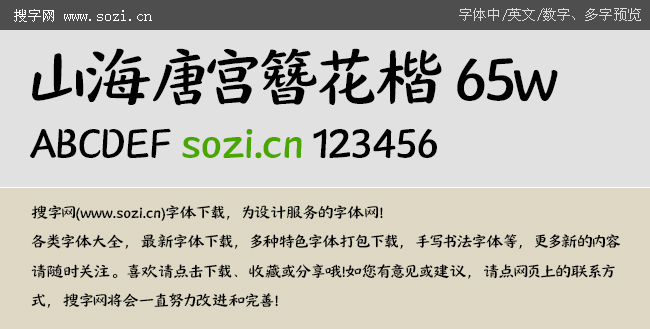
山海唐宮簪花楷 65w
搜字網給大家提供一款山海唐宮簪花楷 65w中文字體下載,山海唐宮簪花楷是一款全新的楷體字體,該字體字形優美文雅,禪韻內斂,取楷體細膩的書寫筆畫,書法的運筆走勢蘊含其中,流暢自然,蘊含東方審美韻味,盡顯優雅從容,秀雅清新,禪韻十足。適用于畫冊設計、海報設計、包裝設計等場合使用。